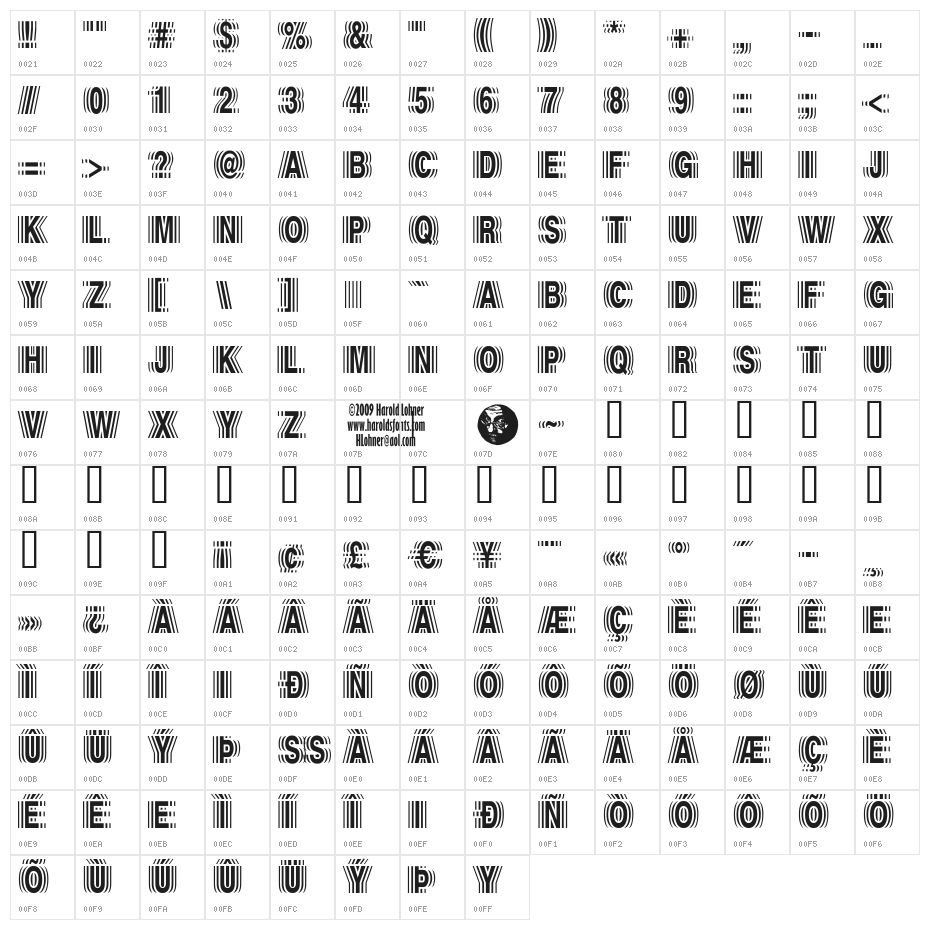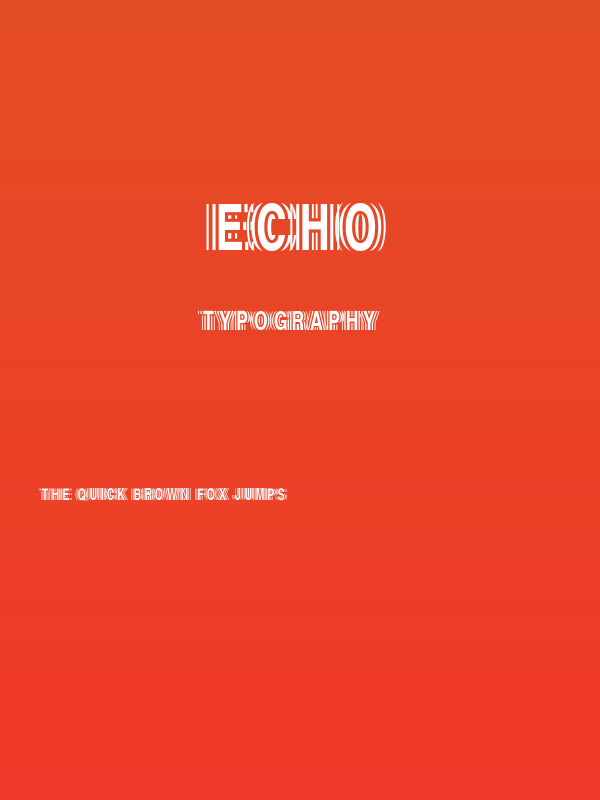
Echo Font
✎ Outline
| Kategorien | Outline |
| Gesamtstil | Modern, Decorative |
| Anwendungsfall | Headlines, Logos, Artistic projects |
| Vorgeschlagene Projekte | Ideal for posters, album covers, branding, and any project requiring a bold, artistic statement. |